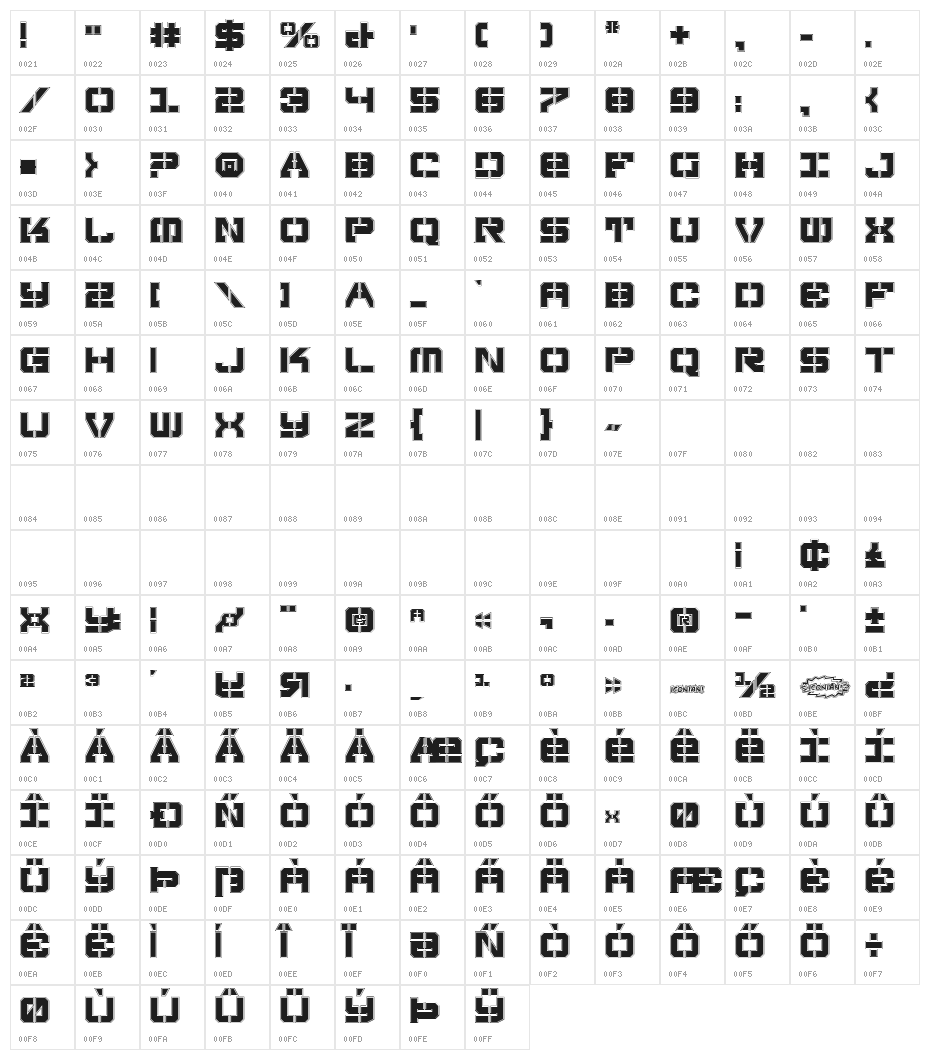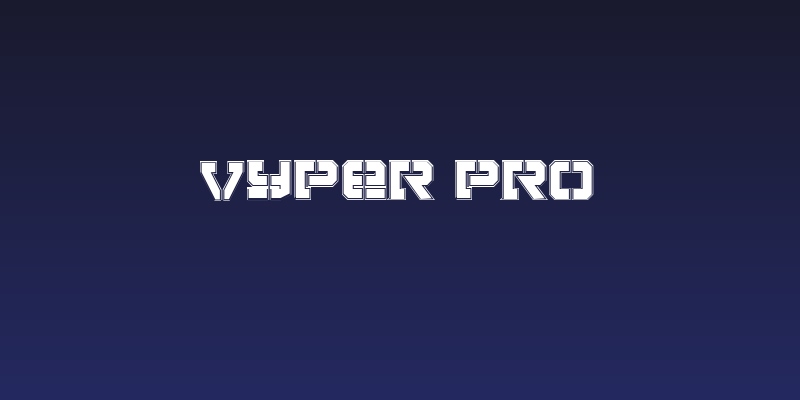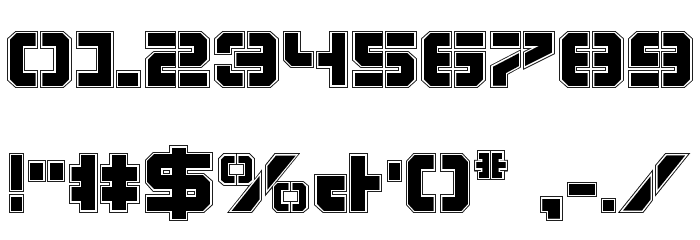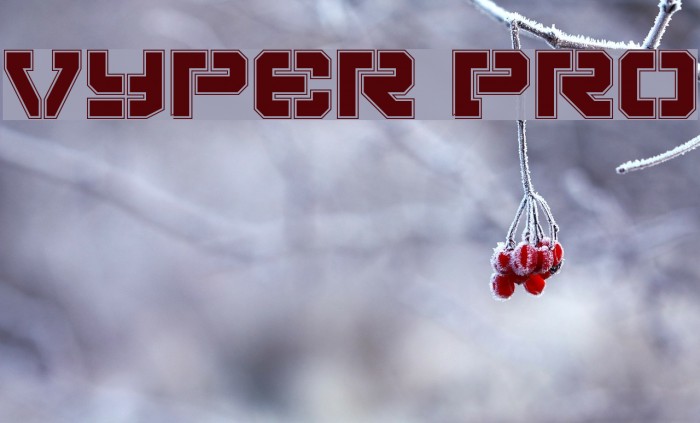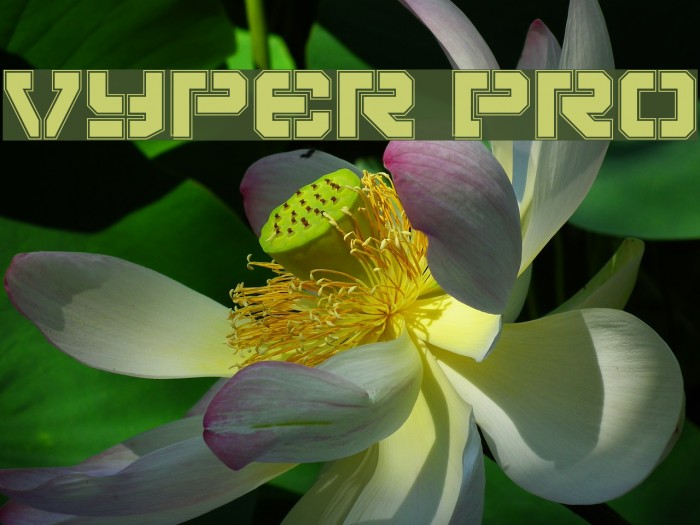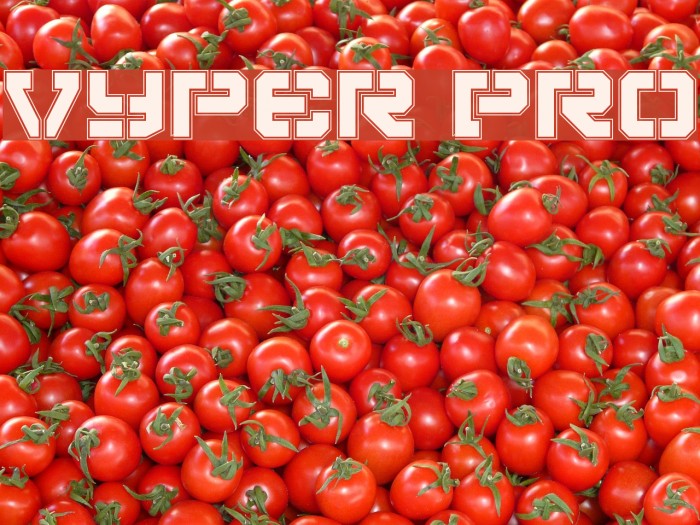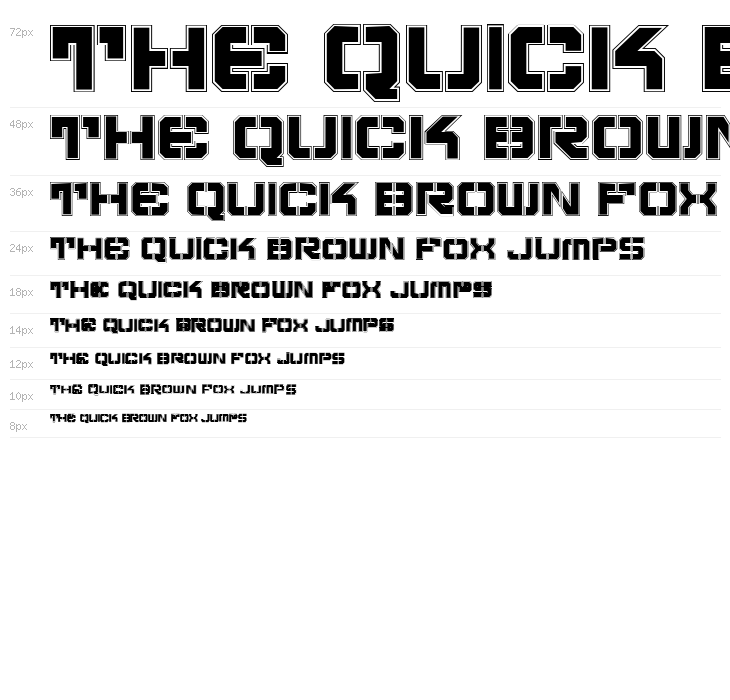
Vyper Pro Font
✎ Sci-fi
| Projets proposés | Ideal for technology-themed projects, video game titles, posters, and branding that requires a modern and impactful look. |